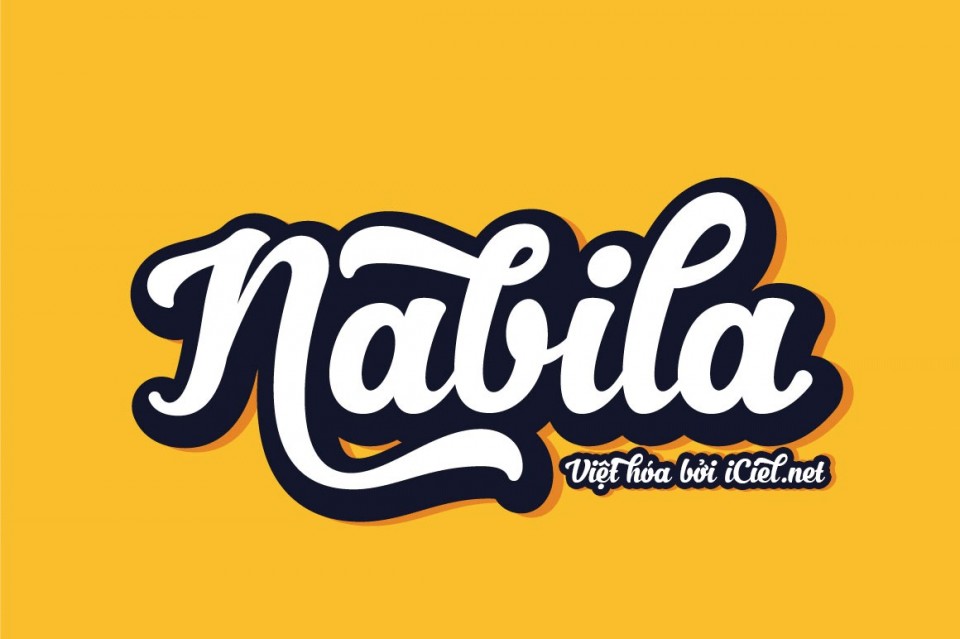
Giới thiệu về Font việt hóa iCiel Nabila
Trong thế giới đồ họa hiện đại, việc lựa chọn một Font Miễn Phí phù hợp là yếu tố then chốt giúp tác phẩm trở nên nổi bật. Font việt hóa iCiel Nabila là một trong những bộ phông chữ Script mang phong cách retro đầy ấn tượng. Với những đường nét uốn lượn mềm mại và dày dặn, bộ phông này gợi nhớ đến những bảng hiệu quảng cáo cổ điển của thập niên trước. Phiên bản iCiel Nabila đã được tối ưu hóa bảng mã tiếng Việt, giúp người dùng dễ dàng sử dụng trên các phần mềm thiết kế phổ biến mà không lo lỗi hiển thị hay thiếu ký tự đặc biệt.
Ưu điểm nổi bật của Font việt hóa iCiel Nabila
Thiết kế linh hoạt và đa dạng
Điểm mạnh nhất của Font việt hóa iCiel Nabila chính là sự kết hợp giữa tính thẩm mỹ và công năng. Phông chữ này đi kèm với hàng loạt ký tự thay thế (alternates) và các nét chữ nối (ligatures) cực kỳ phong phú. Điều này cho phép người thiết kế thỏa sức sáng tạo, biến hóa các dòng văn bản đơn thuần thành những tác phẩm nghệ thuật chữ viết độc đáo. Kiểu dáng vừa hiện đại vừa mang hơi thở cổ điển giúp nó dễ dàng thích nghi với nhiều phong cách khác nhau từ trẻ trung đến trang trọng.
Ứng dụng thực tế trong giáo dục và đời sống
Tại các trường học, giáo viên có thể sử dụng bộ font này để trang trí bìa giáo án, bảng tin hoặc làm thiệp chúc mừng. Trong khi đó, các bạn học sinh có thể dùng nó để làm tiêu đề bài thuyết trình thêm sinh động. Nhờ khả năng hiển thị rõ nét trên cả màn hình và bản in, đây là lựa chọn lý tưởng cho việc thiết kế logo, bao bì sản phẩm hay các poster quảng cáo cần sự thu hút ngay từ cái nhìn đầu tiên.